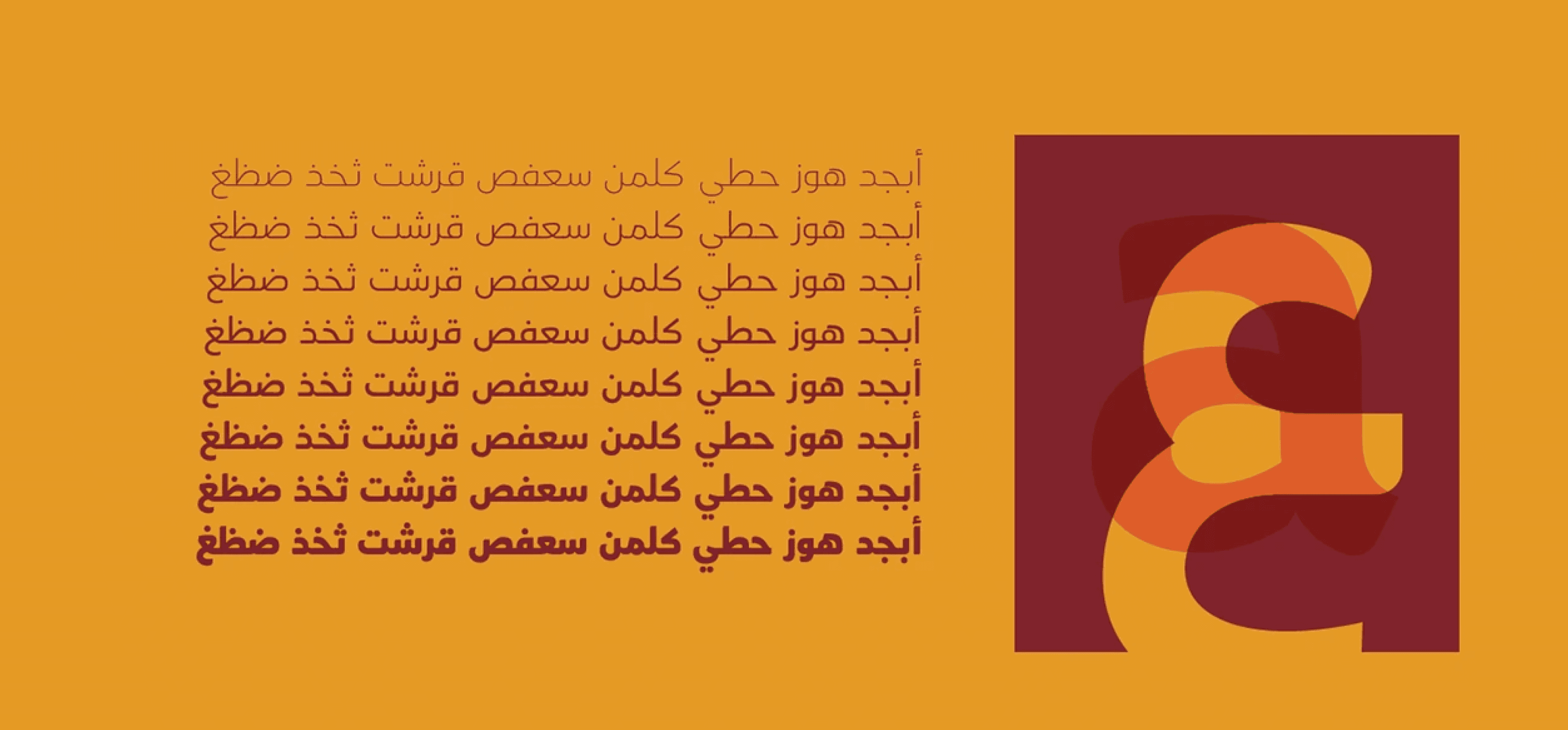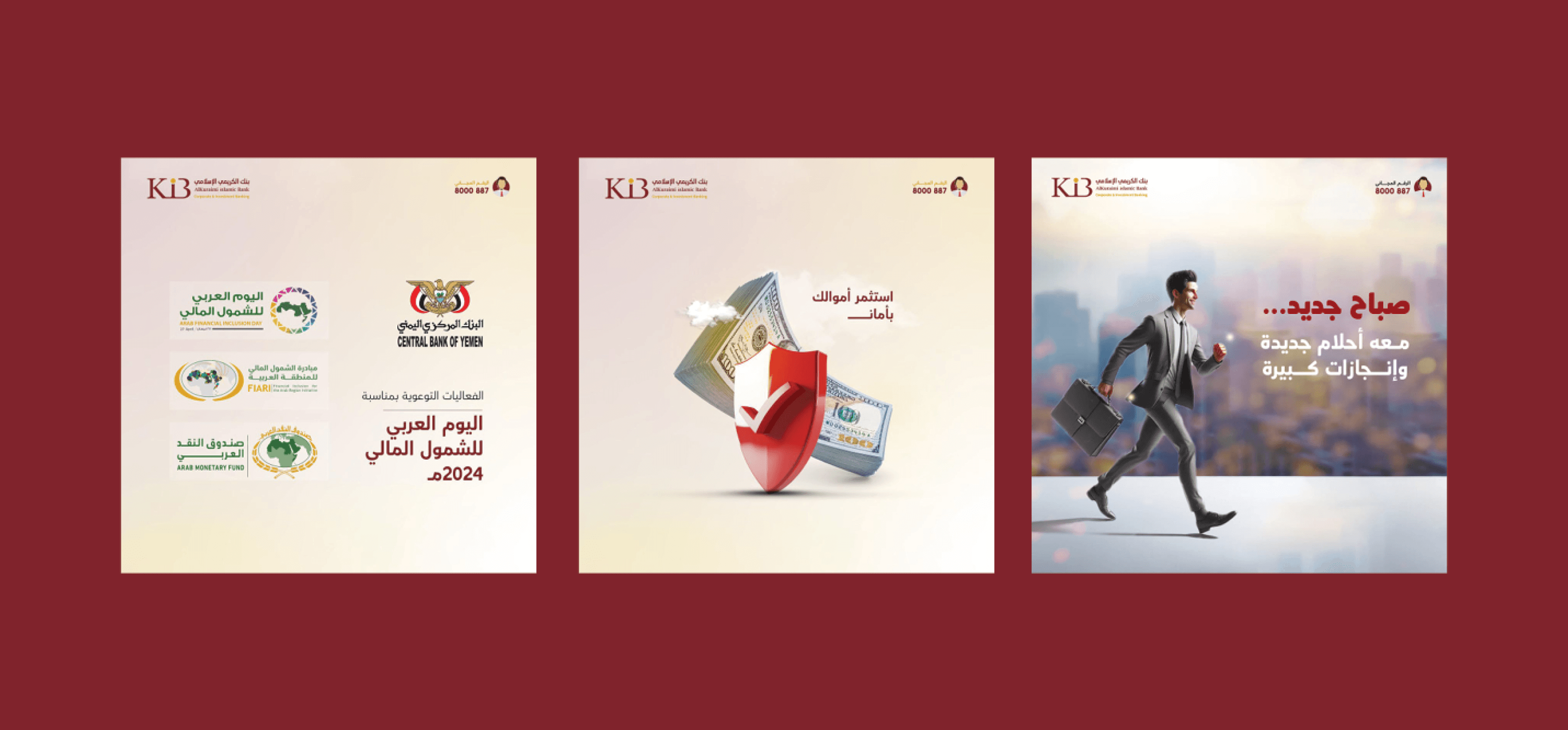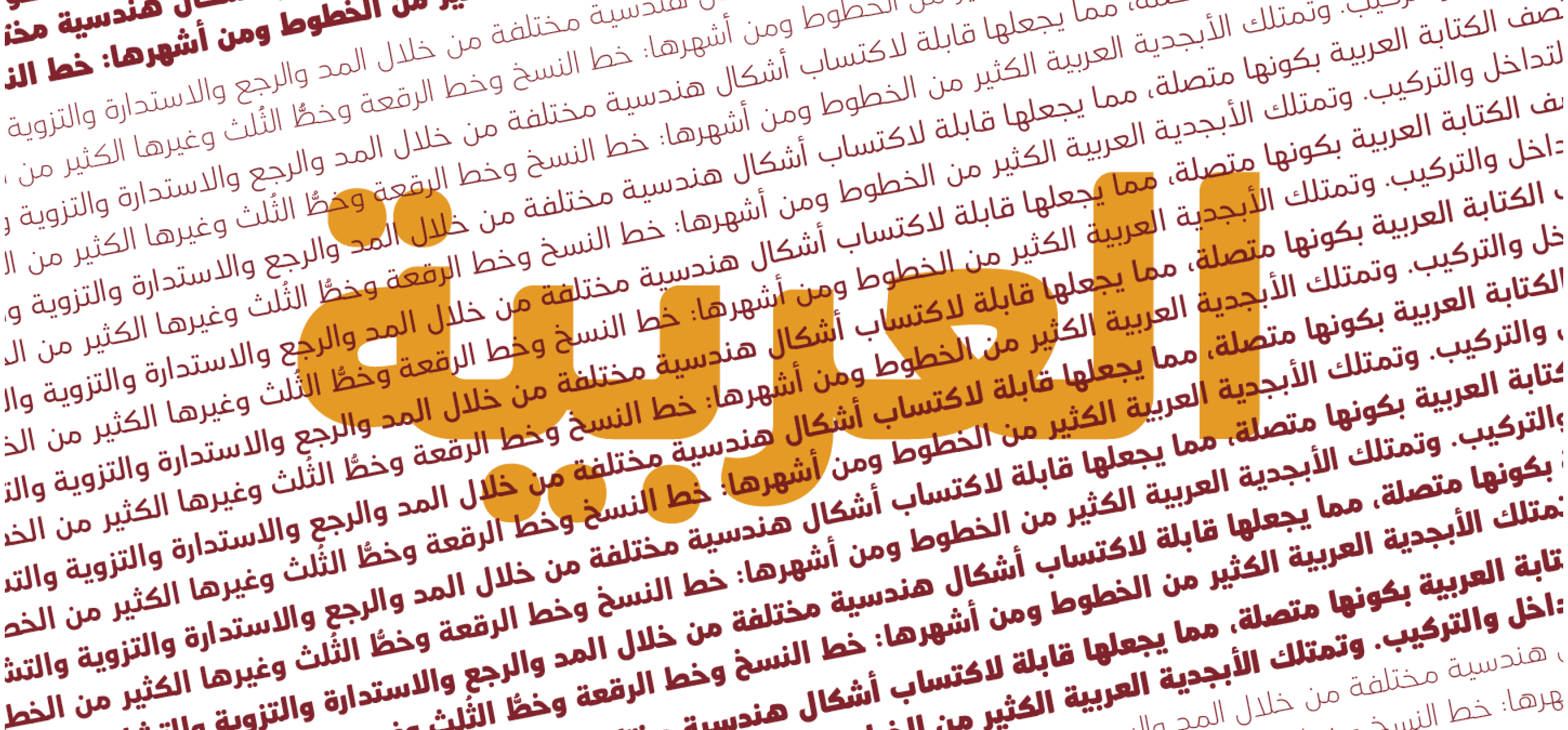
KIBANK TYPEFACE – خط بنك الكريمي الإسلامي
تم تصميم هذا الخط خصيصًا لبنك الكريمي الإسلامي، ليعكس الهوية المؤسسية الحديثة مع الحفاظ على الطابع العربي الأصيل.
يُظهر التصميم دمجًا متقنًا بين البساطة والاحترافية، ويُستخدم الخط باللغتين العربية والإنجليزية لضمان التناسق البصري في الهوية البنكية.
الخلفية المزخرفة بنقوش هندسية إسلامية تضيف طابعًا ثقافيًا مميزًا، بينما يبرز شعار "خط" داخل فقاعة حوار بلون أصفر ذهبي، ما يوحي بالوضوح والتواصل.